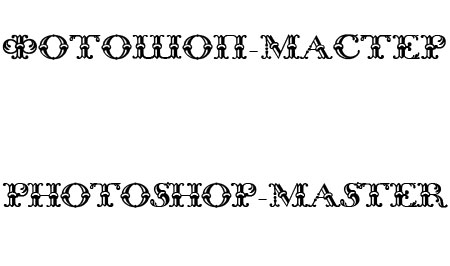
спасибо! как старинный
Мне не сильно понравился шрифт, но при обработке он может очень даже пригодится.
сказочный... возьму, пожалуй, пригодится
шрифт изумительный
Спасибо, прекрасный шрифт.
Прикольный!!!
Этот мне не очень понравился
вот этот очень хороший шрифт!..)
прям как в сказке))
Хороший шрифт, спасибо!
По моему этот шрифт лучший среди всех - да и сайта лучше нет
Очень интересный...